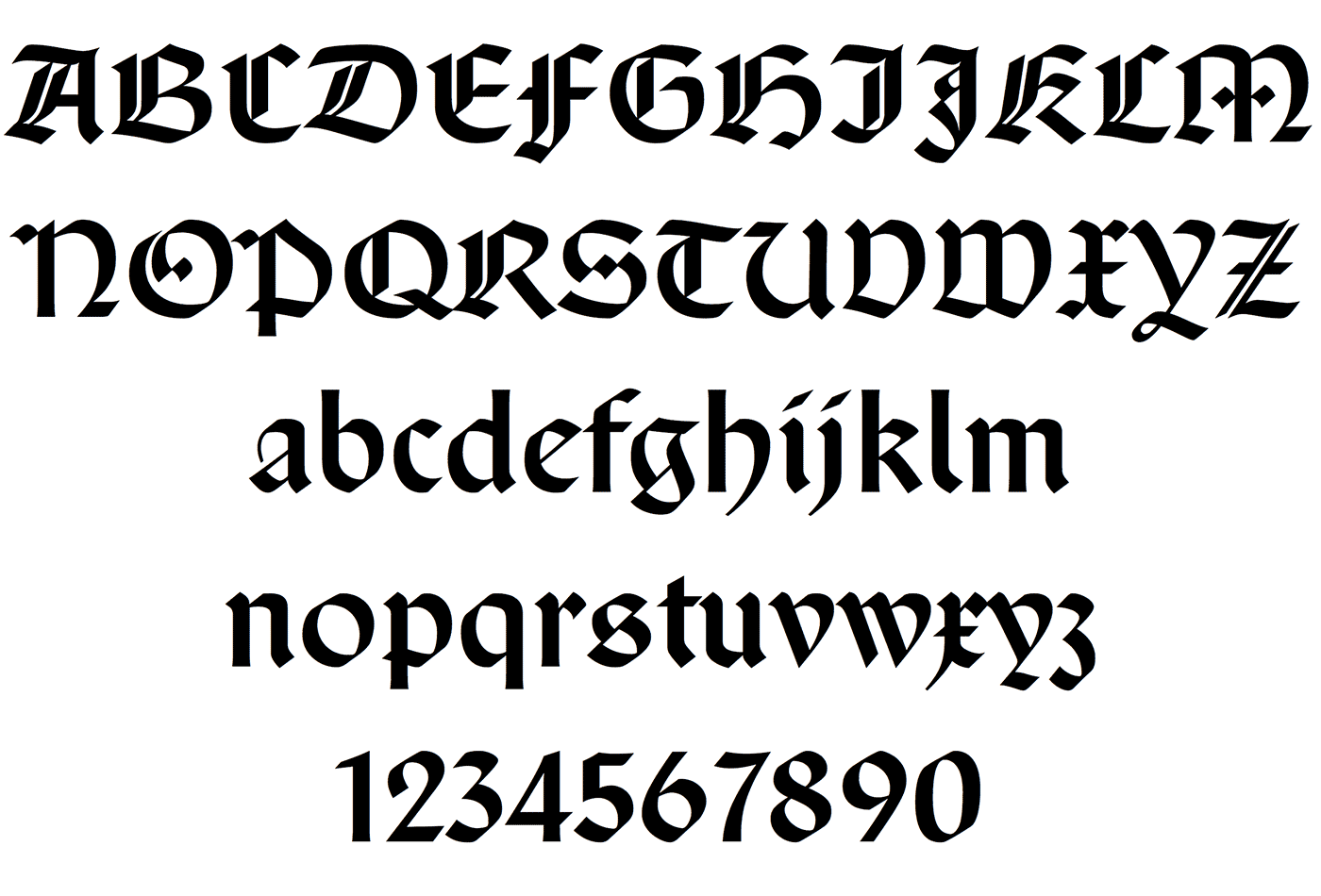
• 1991
• Gebrochene Schrift
Die San Marco ist eine dekorative rundgotische Schrift von Karlgeorg Hoefer. Sie erschien 1991 als Teil der Reihe »Type before Gutenberg«, in der zwölf Schriftgestalter Schriftstile aus der Zeit vor der Erfindung des Drucks mit beweglichen Lettern als Satzschriften interpretierten. Als Vorlage dienten Hoefer die rundgotischen Schriften von Nicolas Jenson aus dem 15. Jahrhundert.
Benannt ist die Schrift nach der San-Marco-Kathedrale im Zentrum Venedigs.